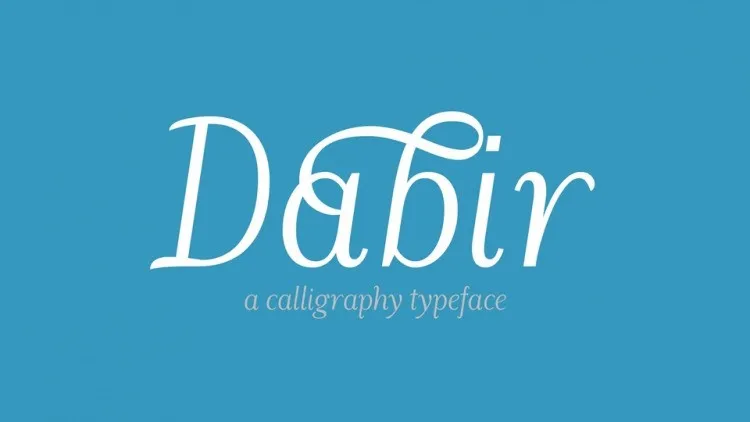
Dabir Font – Download Grátis
Esta é uma fonte sans-serif com letras maiúsculas e minúsculas que possui curvas equilibradas e bem definidas. Foi projetada por Amir Mahdi Moslehi para completar a famosa fonte Dabir. Com suas linhas leves, essa nova versão de Dabir garante um estilo moderno e elegante, perfeitamente adequado para aplicações que precisam de um toque sofisticado e clean. Seja em aplicativos digitais ou em projetos gráficos, a fonte Dabir é uma escolha ideal para designers que buscam uma opção mais minimalista e contemporânea. Essa fonte não só oferece uma experiência visual única, como também se adapta perfeitamente aos estilos de design que valorizam simplicidade e clareza.